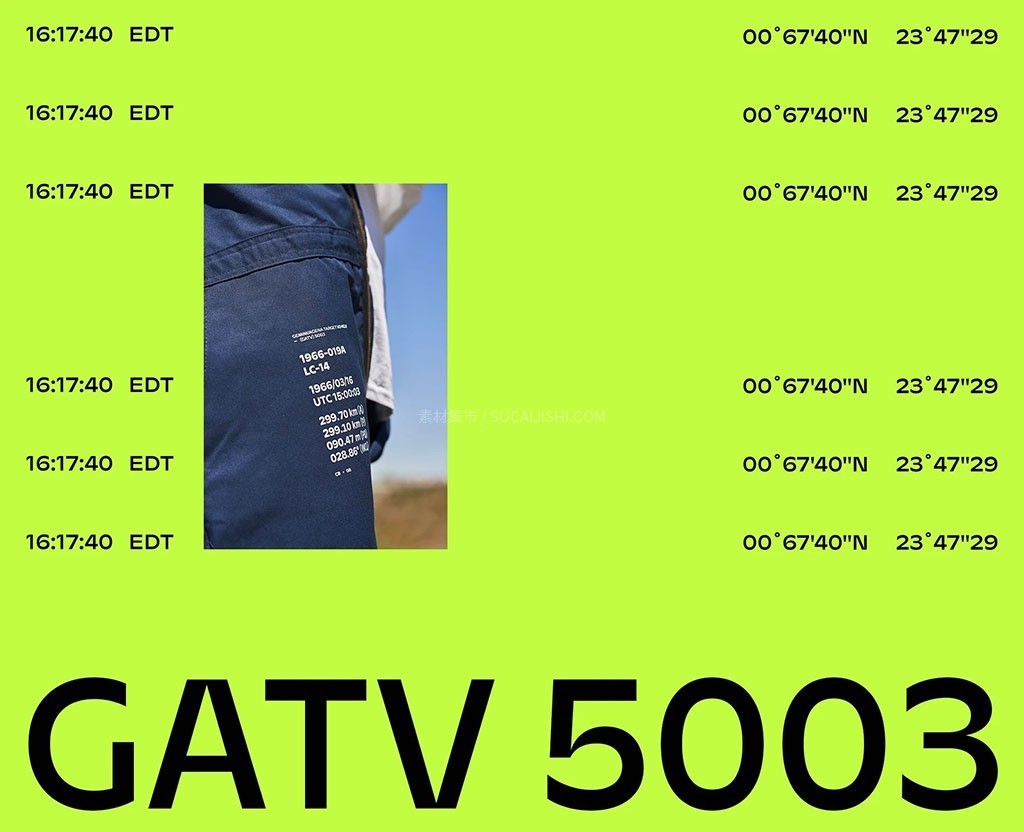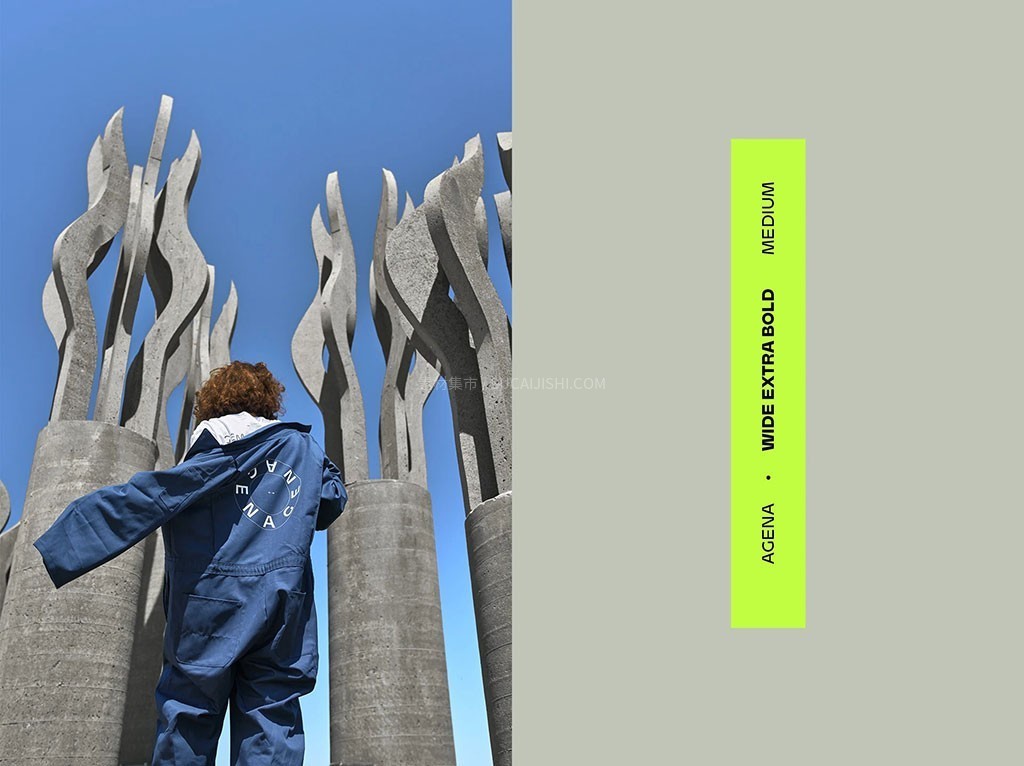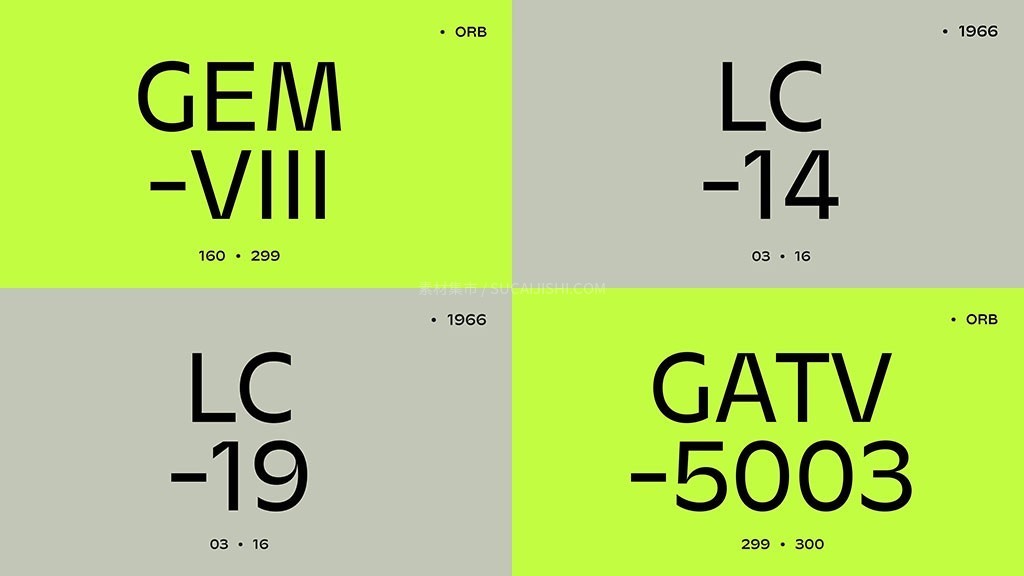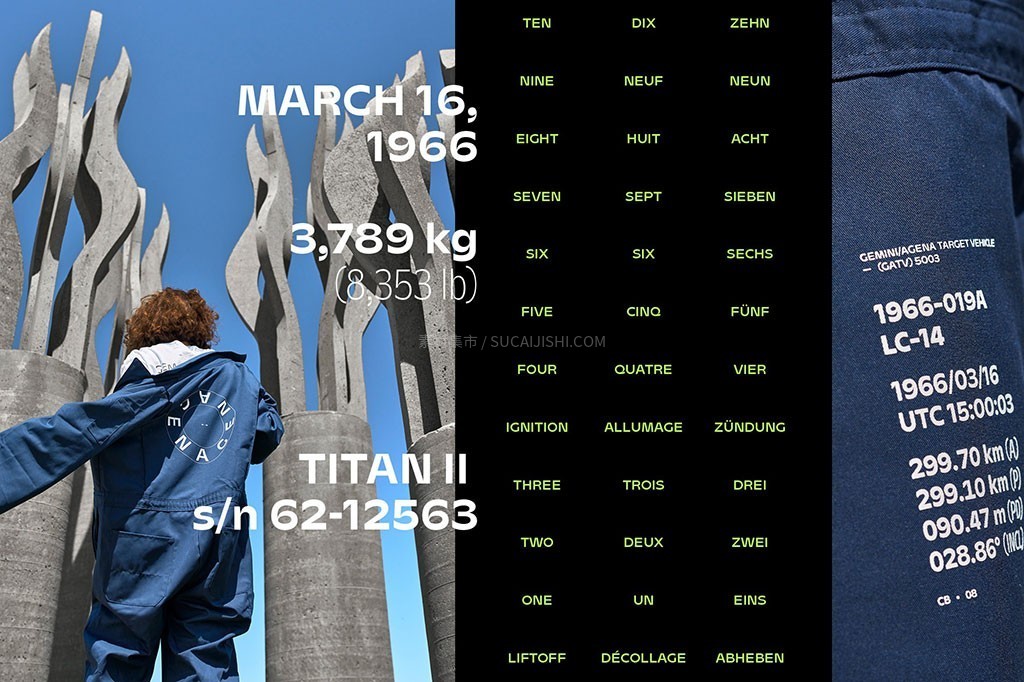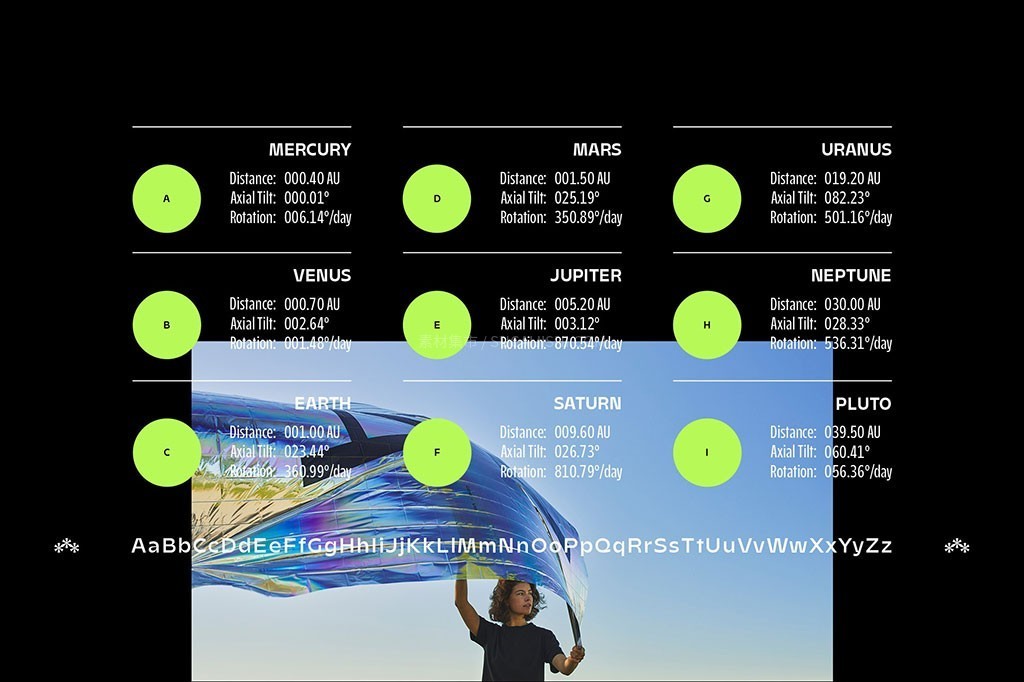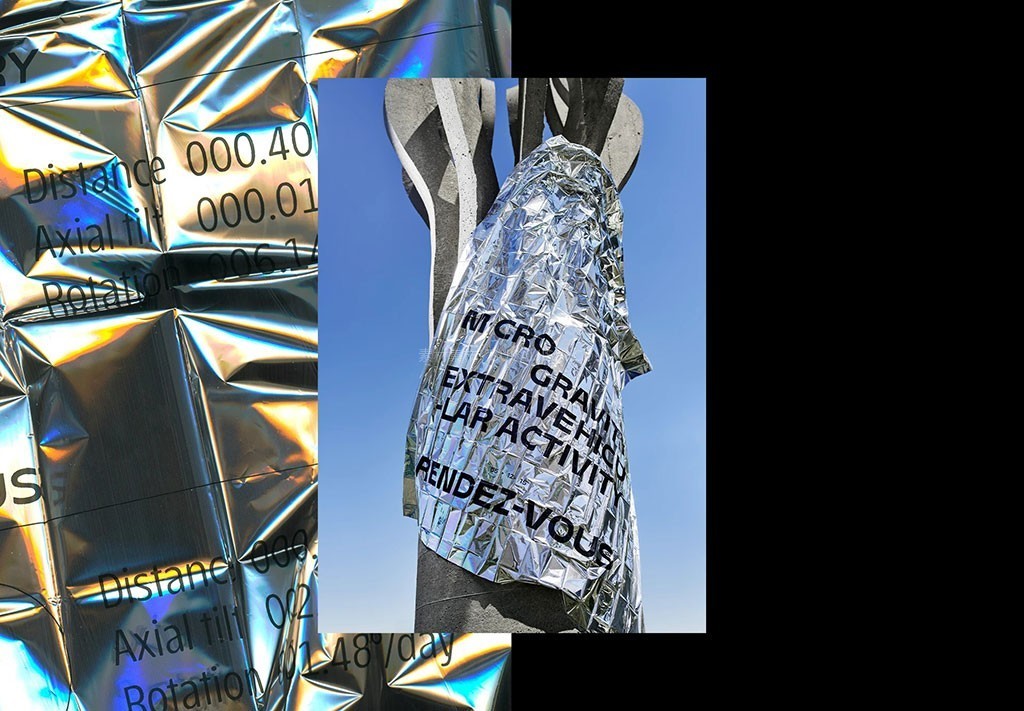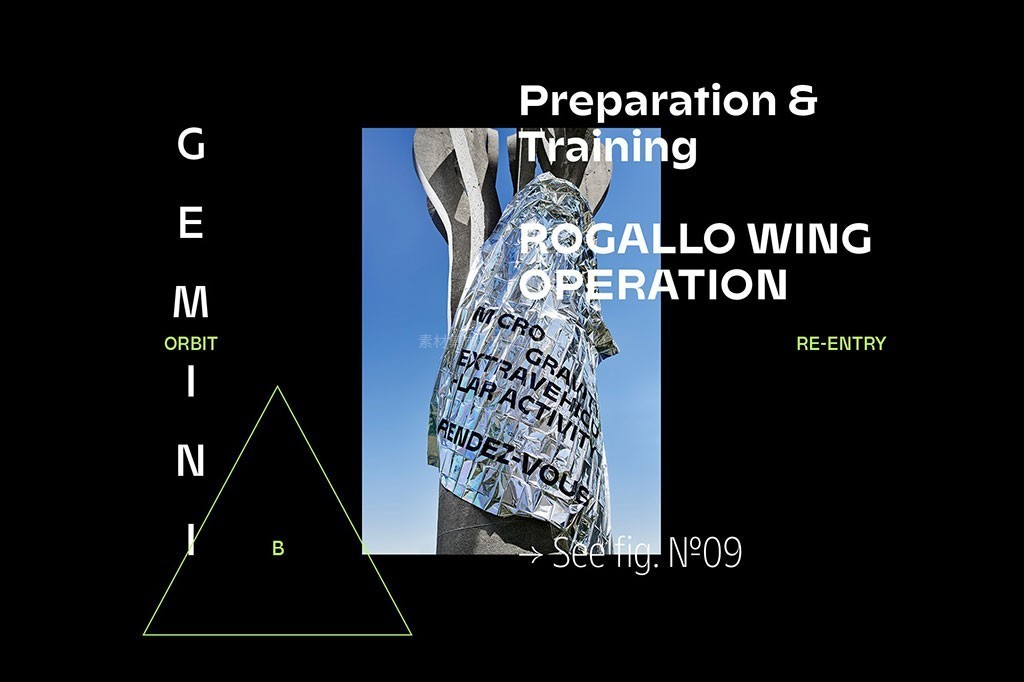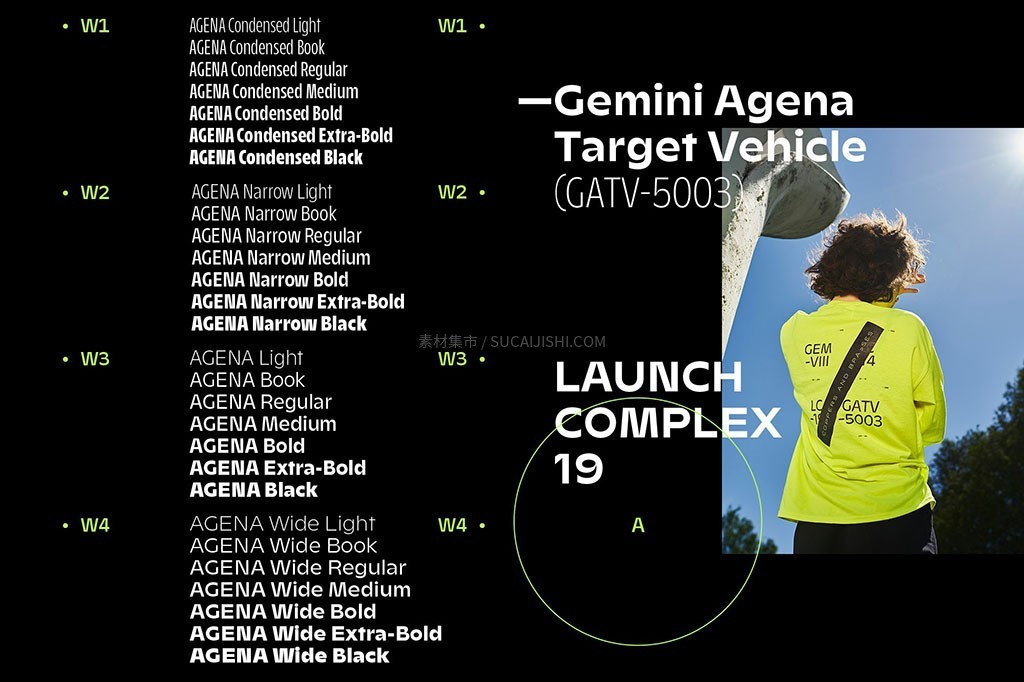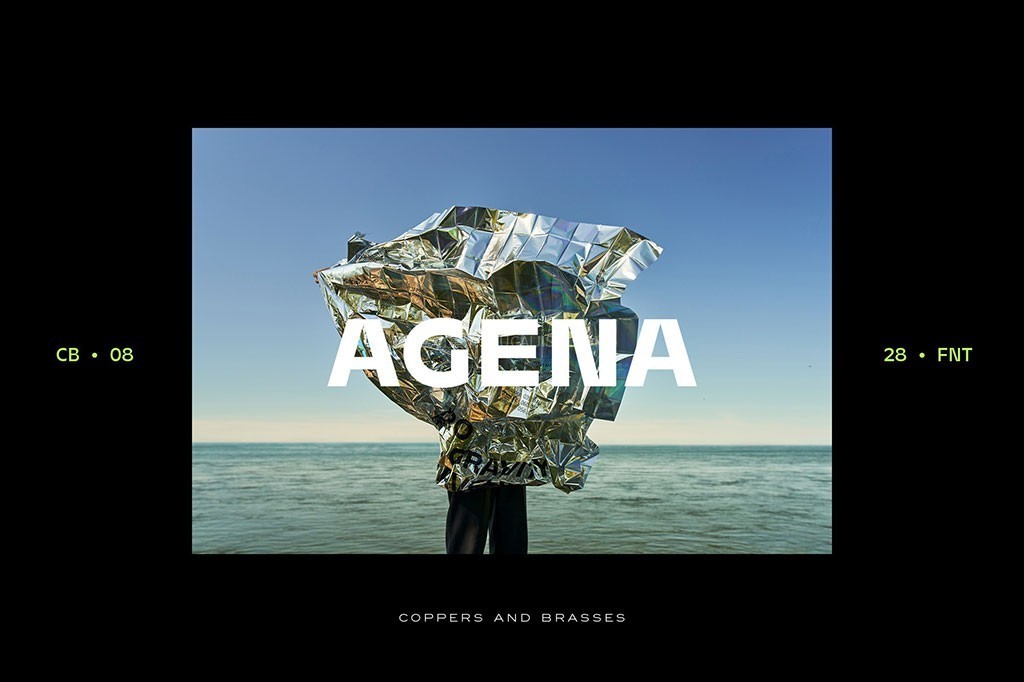
Agena Display 现代几何字体家族(28种字重)
Agena 是一款极具表现力的标题展示字体家族,完美融合了 60 年代人文主义无衬线字的艺术张力与现代几何字体的简约美感。它独特地放大了视觉修正效果,同时保持较低的笔画对比度,字形干净利落且充满设计惊喜。全套包含“压缩、窄版、标准版、宽版”四大系列共 28 种丰富字重与字宽样式,支持随心所欲地自由混搭,为您解锁无限的排版创意,轻松打造极具个性的视觉作品!